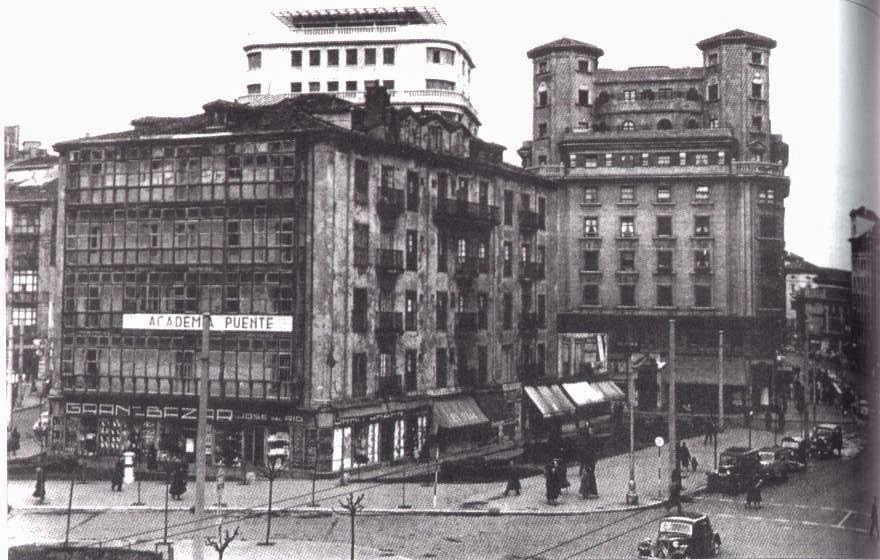
Gran Bazar
Entre los años 40 y 50 donde hoy se ubica la plaza del Ayuntamiento existió un edificio conocido como el SEPI (Sociedad Española de Precios Increíbles) propiedad de Celedonio Gandarillas y que se salvó del incendio del 41. En sus bajo estaba instalado un negocio que tenía inicialmente dicho nombre, pero que cambió al año de abrirse por una demanda de los Almacenes «SEPU» de Madrid. Entonces se pasó a llamar «Gran Bazar de Jose del Río».
Su espectacular rótulo se podría considerar moderno para la época, con una tipografía totalmente geométrica que dominaba su fachada y es el que aquí tenéis reproducido. El edificio fue demolido en los años 60 para empezar a construir la plaza.
Edificio SEPI en 1943. Fuente: Escenas de Santander (https://escenasdesantander.blogspot.com.es/2014/07/un-poco-de-historia-xxxi.html)